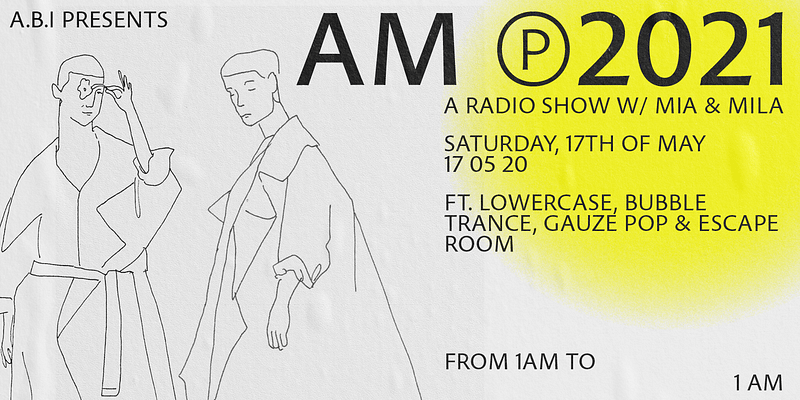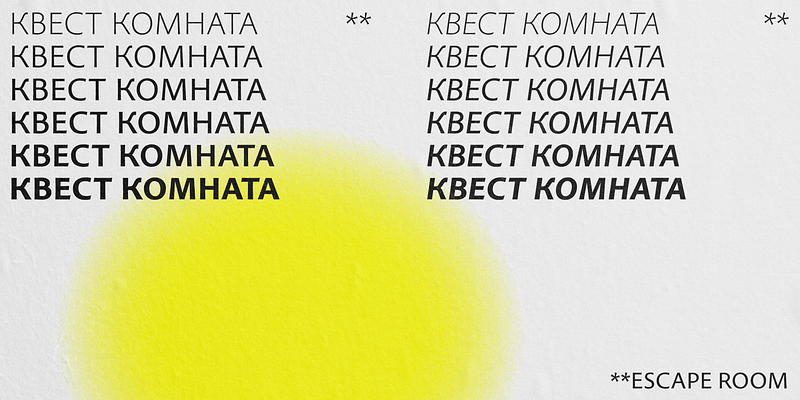
Pelago ist eine halbformale serifenlose Schriftfamilie von Adobe Principal Designer Robert Slimbach. Die Familie hat ein klares, modernes Erscheinungsbild und eine unaufdringliche Eleganz.
In Display-Größen zeigt Pelago subtil anschwellende Strichabschlüsse, animierte Buchstaben-Gegenformen und einen moderaten Grad an Strichmodulation – Qualitäten, die sowohl von humanistischen Handschriften als auch von römischen Inschriften stammen. Bei kleineren Schriftgrößen treten diese ausdrucksstarken Akzente zurück und geben den Blick frei auf ein klares und sehr gut lesbares Schriftbild, das nicht unter der strukturellen Starrheit leidet, die bei herkömmlichen serifenlosen Designs auftritt.
Pelago wird in einer Reihe von sechs Strichstärken mit passenden Kursivschnitten und mit einer breiten Sprachabdeckung einschließlich Griechisch, Kyrillisch und erweitertem Latein angeboten.